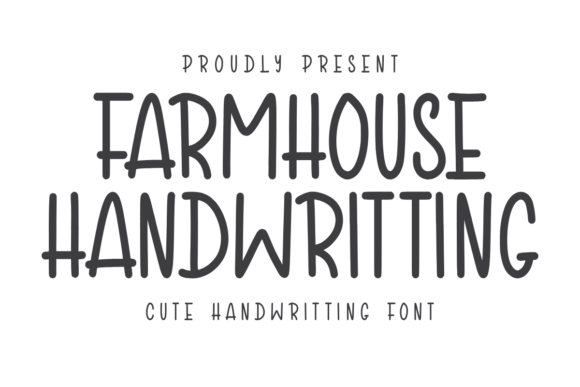
Farmhouse Handwriting
Het vinden van de juiste ontwerpelementen kan lastig zijn, maar Farmhouse Handwriting biedt een uitzonderlijke collectie die uw werk direct naar een hoger niveau tilt.
Of u nu POD-producten (Print on Demand), huwelijksuitnodigingen of afbeeldingen voor sociale media maakt, Farmhouse Handwriting is een ideale keuze.